「ダーク系」にぴったりの日本語フリーフォント
今回は、不気味さ・退廃・陰影のある世界観を演出できる「ダーク系」の日本語フリーフォントをご紹介します。
闇落ち、ダーク系、ダークファンタジー、耽美系など、フォントにも深みや異様さが求められる場面もあります。
滲んだような筆跡、鋭く冷たい印象の文字、崩れた輪郭や黒の余白が効いたデザインなど、フォントから不安や緊張を感じさせることで、作品の世界観を強く印象づけてくれることができます。
今回は、タイトルロゴや同人誌、MVのリリック、ZINEの表紙、企画の告知などにぴったりな、闇と美しさが共存するダーク系日本語フリーフォントをピックアップしてご紹介します。
不気味で美しい。ダーク系にぴったりな日本語フリーフォント
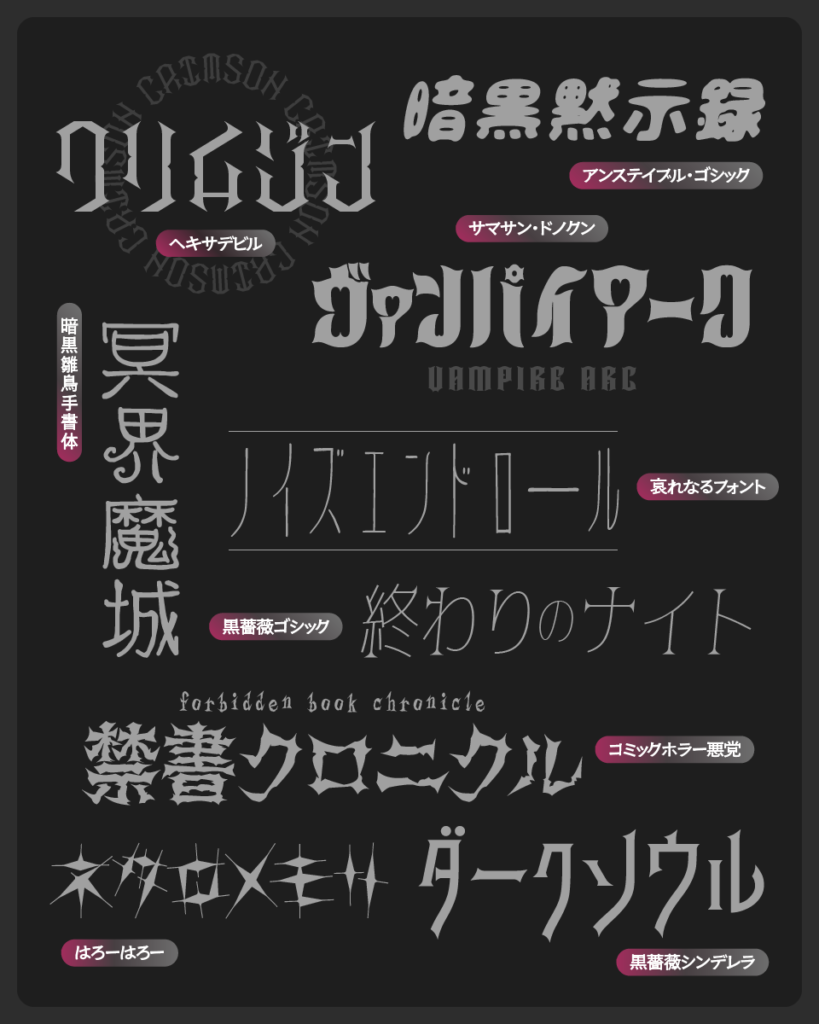
流怪譚
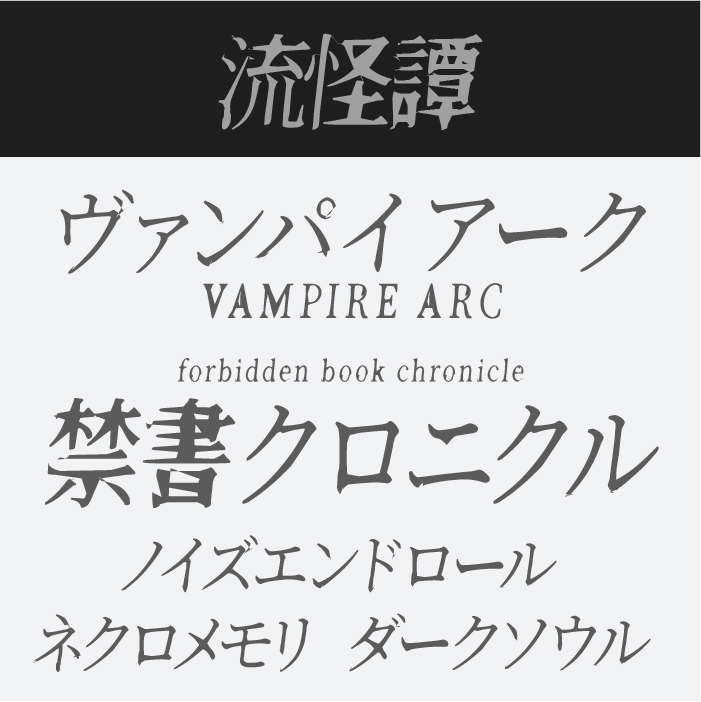
流怪譚フォントは、筆のかすれや揺らぎが特徴の和風ホラーフォントです。どこか古びた雰囲気と恐怖の静けさを感じさせるタッチがあり、怪談や妖怪を題材にした作品と相性の良いフォントです。
白光明朝
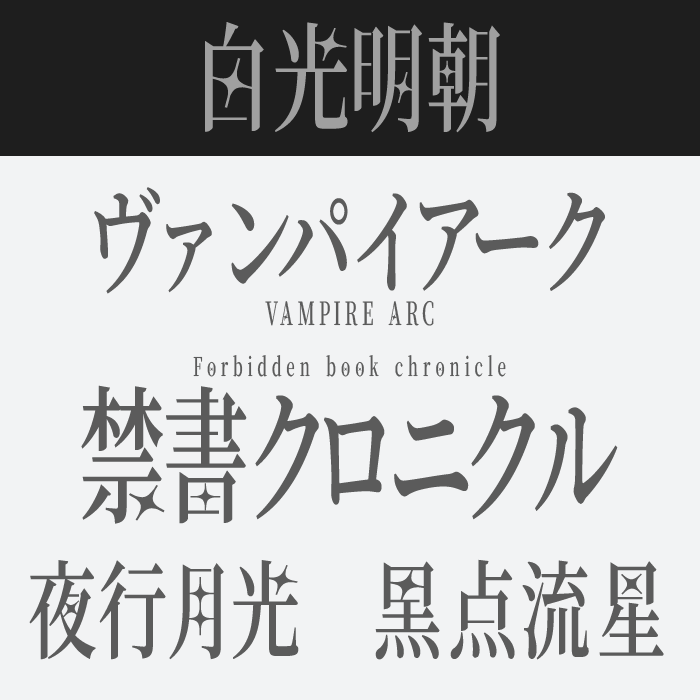
白光明朝フォントは、Noto Serifをベースにしながら、長体+スリット加工を加え、ところどころにキラリとした星の装飾された個性的な明朝体フォントです。
月光やダークヒーローのような世界観にぴったりです。
コミックホラー悪党
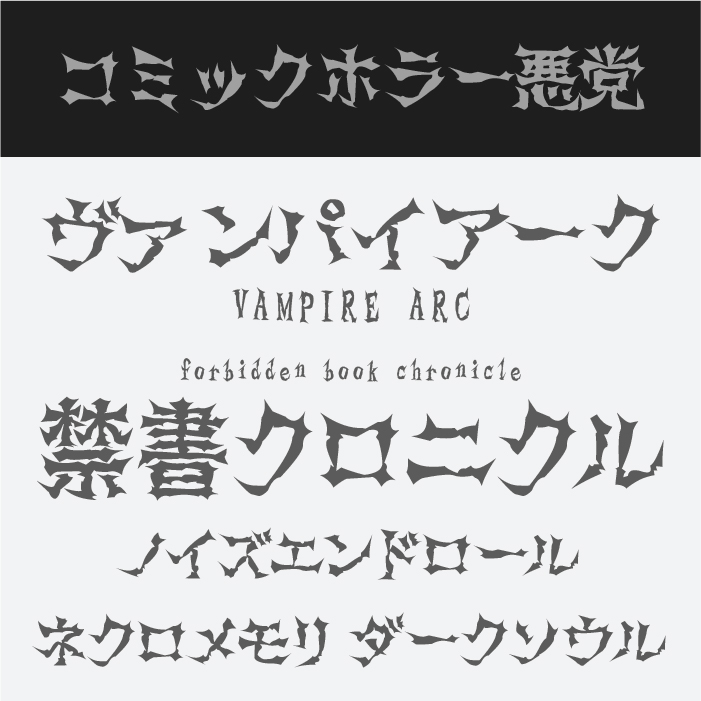
コミックホラー悪党フォントは、鋭いトゲのような装飾が文字に散りばめられた、不気味さと迫力を兼ね備えたフォントです。ホラーやダークヒーロー系な世界観によく合い、血塗られた物語や呪われたタイトルロゴなどにぴったりなフォントです。
黒薔薇シンデレラ
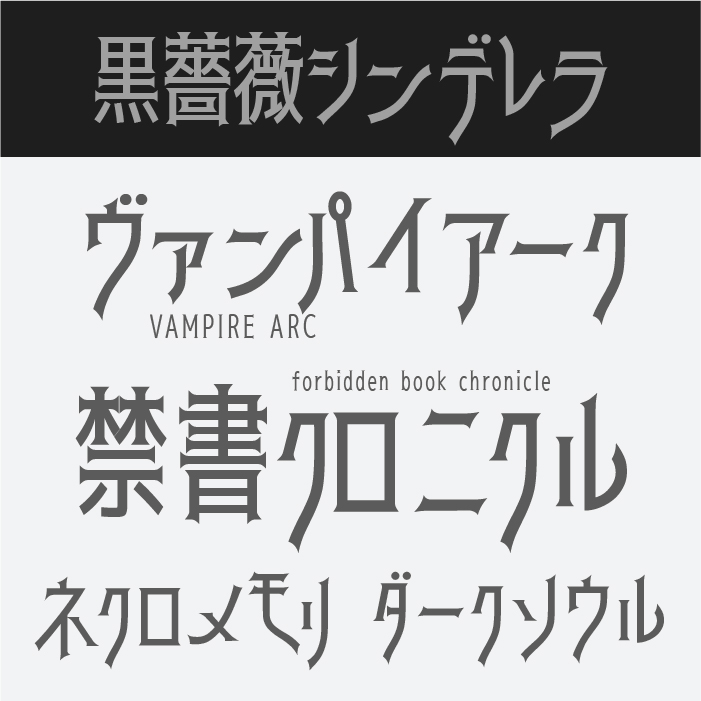
黒薔薇シンデレラフォントは、クラシカルな書体に鋭く尖ったセリフを加えた、退廃的でロマンチックな印象のフォントです。お嬢様系・吸血鬼・アンチヒーローなど作品にぴったりなフォントです。
黒薔薇ゴシック
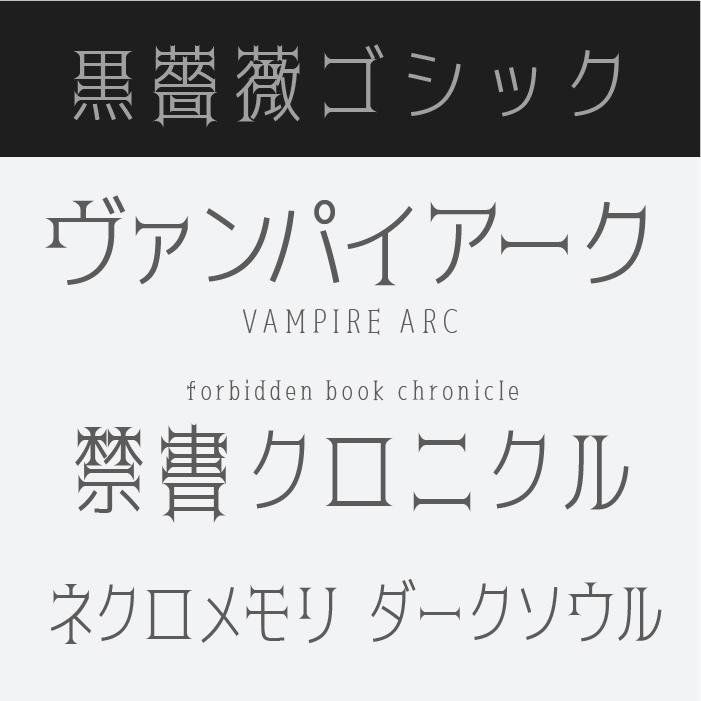
黒薔薇ゴシックフォントは、細身で上品な骨格にヴィクトリアン調のムードが漂う洗練されたデザインが特徴です。静謐な中に潜む恐怖や美しさを表現するのにぴったりなフォントです。ウェイトが複数用意されているので、細いウェイトをだとダーク系を感じます。
暗黒雛烏手書体
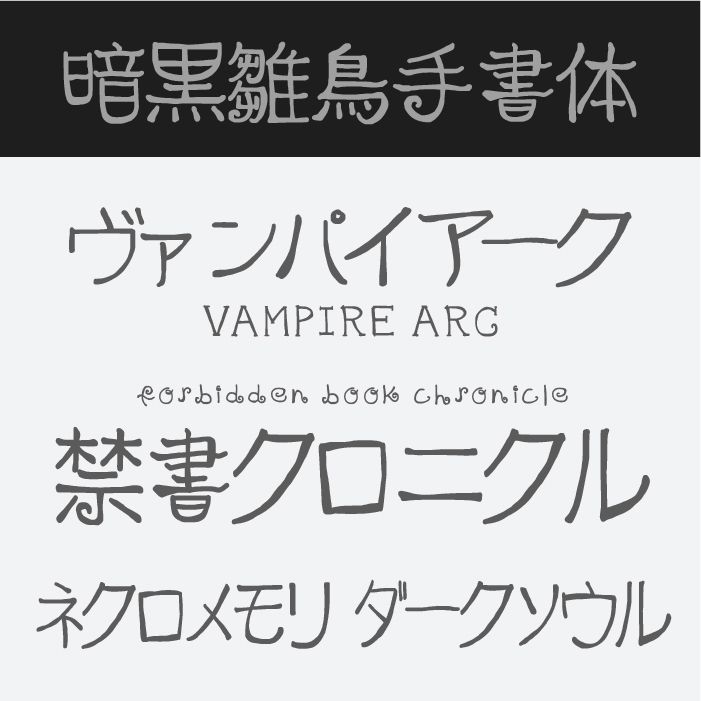
暗黒雛烏手書体は、不揃いでガタついた線が印象的なホラーテイストの手書きフォントです。歪みや不気味さが漂い、呪文や禁忌の言葉、怪しい手記などの演出に効果的なフォントです。
アンステイブル
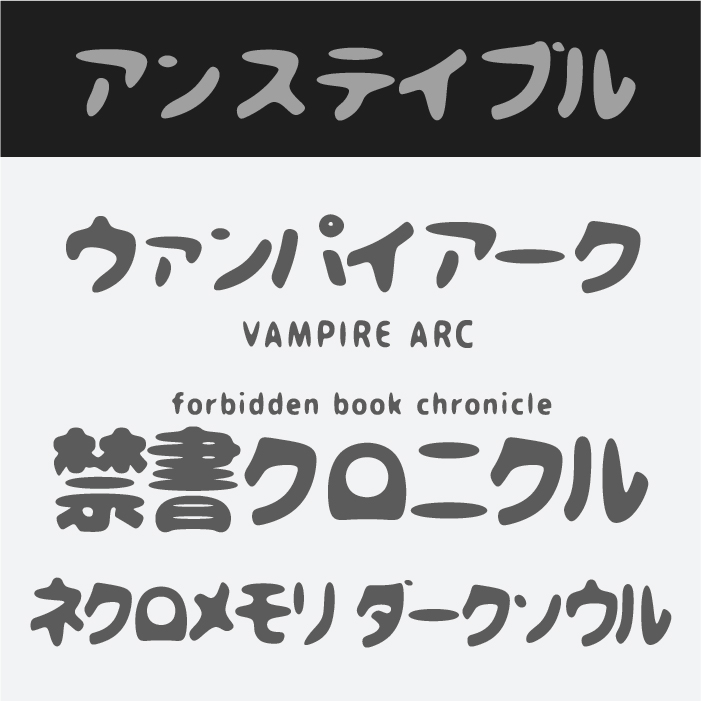
アンステイブルフォントは、柔らかく膨らんだフォルムの中に不安定さが宿る、可愛さと不気味さが混じったフォントです。ダークファンタジーや不可思議な童話などに向いたユニークなフォントです。
ハリガネーゼ
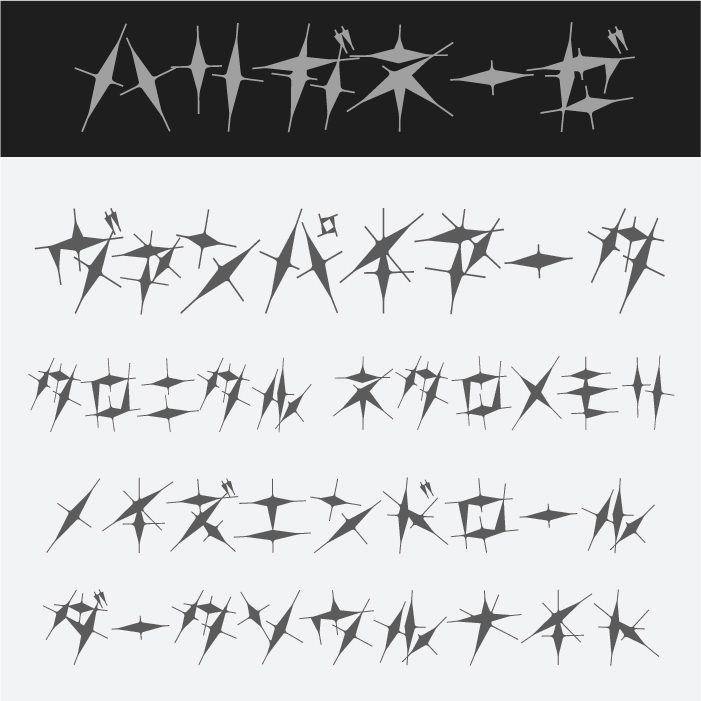
ハリガネーゼフォントは、文字の形自体が星型や棘のように歪んでおり、判読性を犠牲にしてでも恐怖感や異質さを強調する個性的なデザインです。アクセントとして、ダークバトル系や異界を描く世界観にぴったりなフォントです。
哀れなるフォント
哀れなるフォントは、か細く長いストロークが不安や孤独を感じさせる儚げなフォントです。廃墟や幻想的なストーリー、夜闇に沈むような場面にフィットする繊細な雰囲気が魅力のフォントです。
サマサン・ドノクン
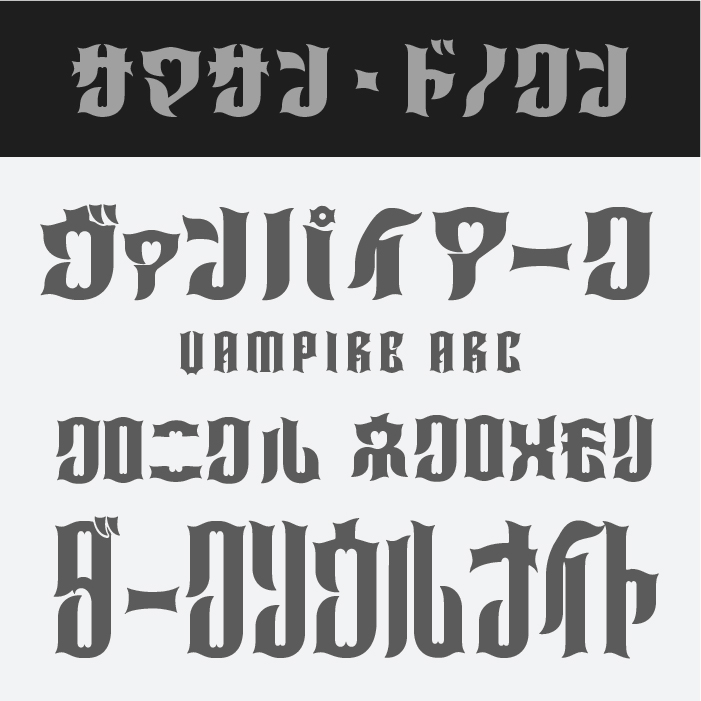
サマサン・ドノクンフォントは、重厚なゴシック体をベースにしたデザインで、荘厳さと暴力性をあわせ持った力強いフォントです。退廃的で破滅的な世界観に重みを加えてくれるフォントです。
ヘキサデビル
ヘキサデビルフォントは、縦長の鋭いシルエットと黒々とした塗りが特徴で、冷たく無機質な印象が強調されています。禁忌の研究施設や機械仕掛けの悪魔的演出にぴったりなフォントです。